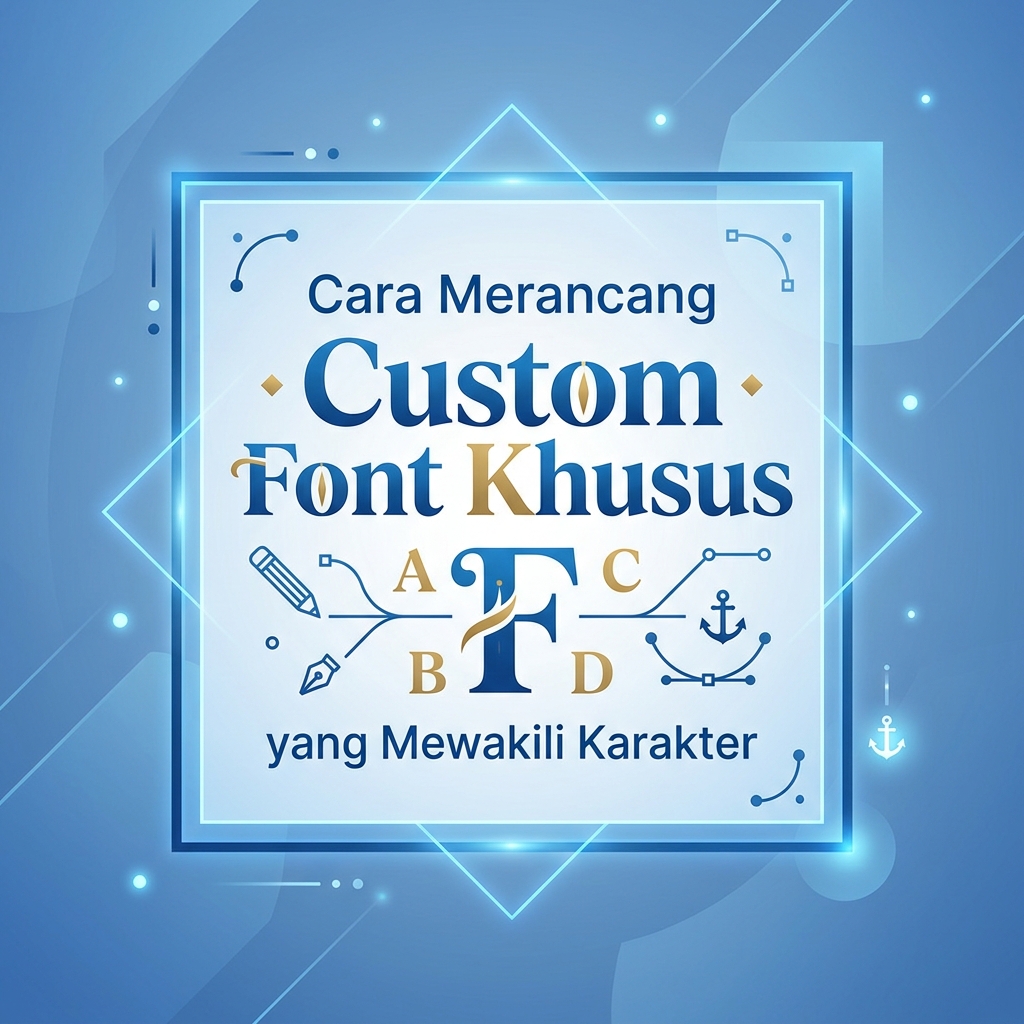
Gubuku – Bayangin punya font khusus yang pas dilihat orang, mereka langsung mikir: “Wah, ini sih vibes-nya dia banget!” Nah, merancang font buatan sendiri itu ternyata nggak seribet yang kamu bayangin. Yuk, simak cara bikin custom font yang standout dan mewakili karakter kamu!
1. Tentukan “Vibes” & Karakter Utama
Sebelum masuk ke aplikasi desain, kamu harus tahu dulu kepribadian apa yang mau disampaiin lewat bentuk tulisan. Font itu punya body language-nya sendiri!
Sans-Serif Geometric: Cocok buat kamu yang serba minimalis, modern, dan clean.
Handwriting / Script: Pas banget kalau mau nampilin kesan santai, estetik, friendly, atau agak rebellious.
Display / Futuristic: Bikin font kamu kelihatan out of the box, ekspresif, dan futuristik.
2. Coret-coret Dulu (Sketsa Manual)
Nggak usah langsung pusing mikirin software pro. Ambil kertas dan pulpen, terus mulai coret-coret bentuk huruf dasar (A, E, O, R, S biasanya paling enak buat eksperimen bentuk). Jangan takut jelek! Di tahap ini, kamu cuma perlu nyari bentuk garis, lekukan, atau sudut unik yang mau jadi ciri khas utama font kamu.
3. Digitalisasi Pakai Software Vector
Begitu dapet sketsa yang pas, saatnya bawa karya kamu ke alam digital. Kamu bisa scan atau foto sketsa tadi, lalu masukin ke aplikasi vector kayak Adobe Illustrator, Figma, atau Inkscape (versi gratisan).
Tips Pro: Gunakan Pen Tool buat menjiplak sketsa kamu biar garisnya mulus. Pastikan ketebalan (stroke) antar-huruf konsisten biar kelihatan rapi pas diketik.
4. Ubah Vector Jadi Font Beneran
Biar tulisan kamu bisa diketik di HP atau laptop, file vector tadi harus diubah jadi format font (.otf atau .ttf). Kamu bisa pakai beberapa platform simpel ini:
Calligraphr: Paling ramah pemula! Tinggal cetak template, tulis tangan di kertas, foto, lalu upload.
Fontself: Extension buat Adobe Illustrator/Photoshop. Tinggal drag and drop huruf yang udah kamu buat, langsung jadi font.
Glyphs / FontLab: Buat kamu yang mau serius dan butuh fitur typography kelas berat.
5. Lakukan Test Drive!
Jangan langsung sebarin ke temen-temen sebelum di-tes. Coba ketik kalimat panjang (typing test) buat liat apakah jarak antar-huruf (kerning) udah pas atau masih berantakan. Coba juga gabungan kata-kata unik buat memastikan font kamu tetap gampang dibaca.
Bikin custom font itu cara paling cool buat nunjukin identitas kamu di dunia digital. Selain bikin karya kamu makin estetik, font unik ini juga bisa jadi aset komersial yang bernilai mahal, lho!